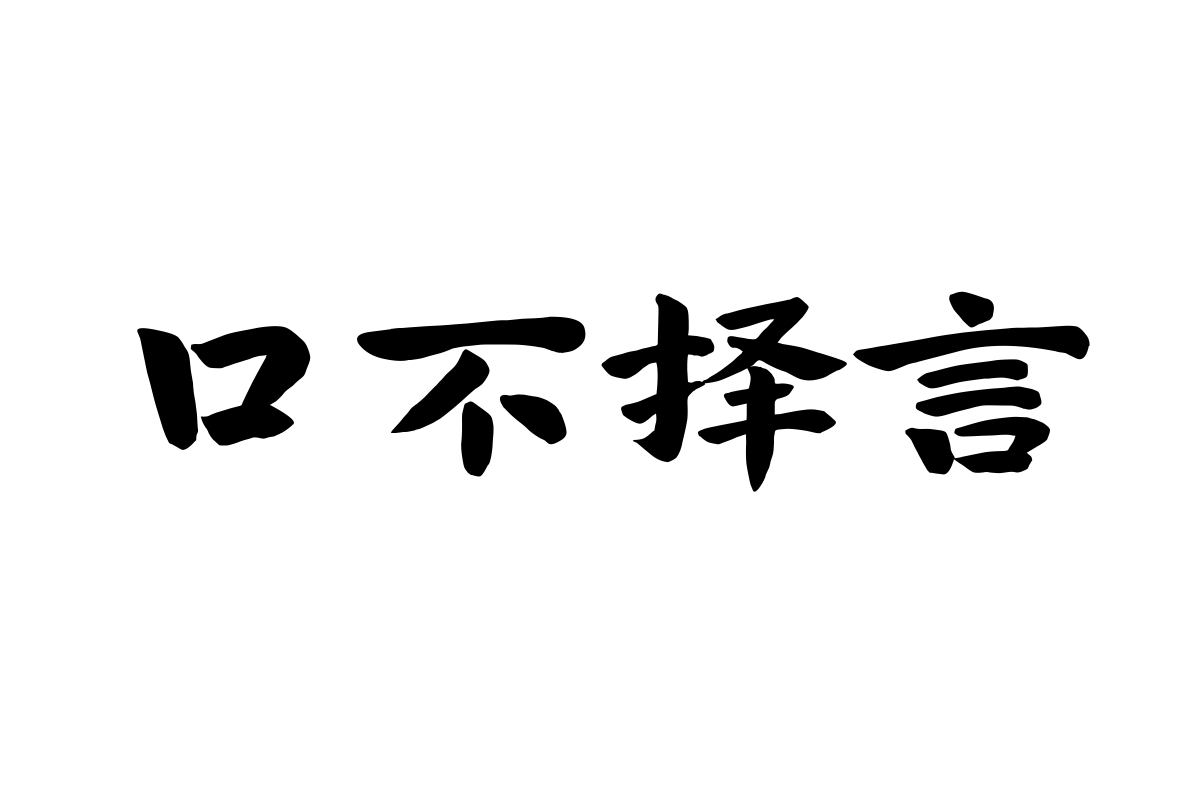
汉仪杰龙古楷是一款具有深厚文化底蕴的字体。它的字形端庄、结构严谨,线条流畅,给人以古朴典雅的感觉。这款字体适合用于书写古籍、碑文等需要体现传统文化韵味的场合。
汉仪杰龙古楷的特点在于其笔画的粗细变化和结构的层次感。它既有隶书的规整性,又有楷书的流畅性,使得整体视觉效果既庄重又不失灵动。同时,这款字体还注重细节的处理,如笔锋的变化、字间距的调整等,都体现了作者对书法艺术的深刻理解和精湛技艺。
总的来说,汉仪杰龙古楷是一款非常适合用于传统文化传播与展示的字体。无论是在书籍装帧、海报设计还是网页排版等方面,都能展现出其独特的魅力。